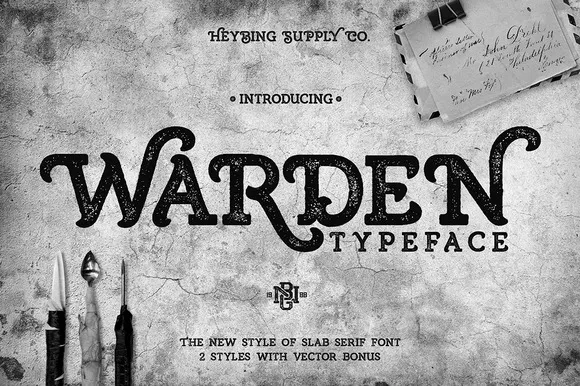
Warden Typeface – Fonte Grátis
Warden Typeface
A Warden Typeface é inspirada no guardião de um presídio, uma figura que assume responsabilidades e cuidados por algo específico. Esta fonte tem um forte carácter de design feito à mão que pode abrigar vários estilos de criação. Ela possui um conjunto de caracteres com um toque simples, retro e vintage, proporcionando uma sensação elegante para qualquer projeto. A fonte vem em dois estilos: um limpo e deslumbrante para criar alternativas únicas para os designs, e o outro é áspero e robusto. Para obter a combinação perfeita, basta misturar maiúsculas com minúsculas e acrescentar as alternativas de caracteres. Uma fonte perfeitamente adequada para quem busca uma paixão retro na sua criação visual.